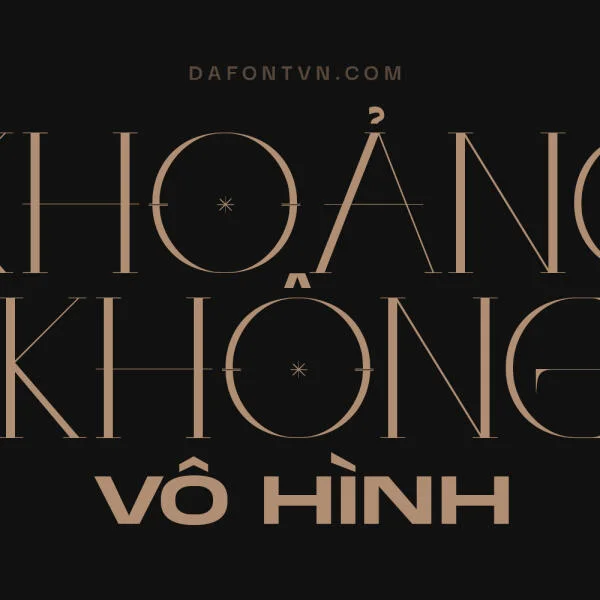
Tổng quan về Font Round Saetan
Round Saetan là kiểu chữ hiển thị lấy cảm hứng từ trang trí nghệ thuật từ thiết kế của nhà thiết kế. Kiểu dáng đẹp, mỏng và đơn giản với hơi hướng hiện đại. Kiểu sans serif được sử dụng bởi phông chữ Round Saetan là phông chữ kiểu 2022, có một sự thay thế swash độc đáo, có nhiều lựa chọn chữ ghép.
Round Saetan rất dễ áp dụng cho bất ký thiết kế nào, đặc biệt là những thiết kế cần sự hiện đại và mới mẻ, ngoài ra font được mã hóa PUA nên rất dễ sử dụng trong hầu hết các chương trình thiết kế và phi thiết kế.
Chi tiết các ký tự Font Round Saetan việt hóa
Round Saetan có 662 glyph với nhiều tùy chọn thay thế độc đáo và thú vị. Thực ra font đã có sẵn dấu nhưng nhiều dấu bị lỗi mình đã sửa lại, kerning, feature và tối ưu lại font cho hoàn chỉnh hơn với dấu tiếng Việt.